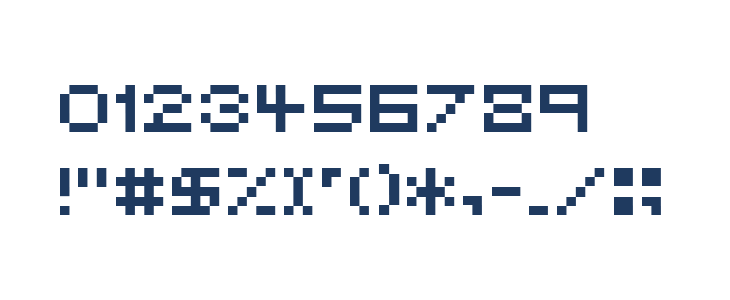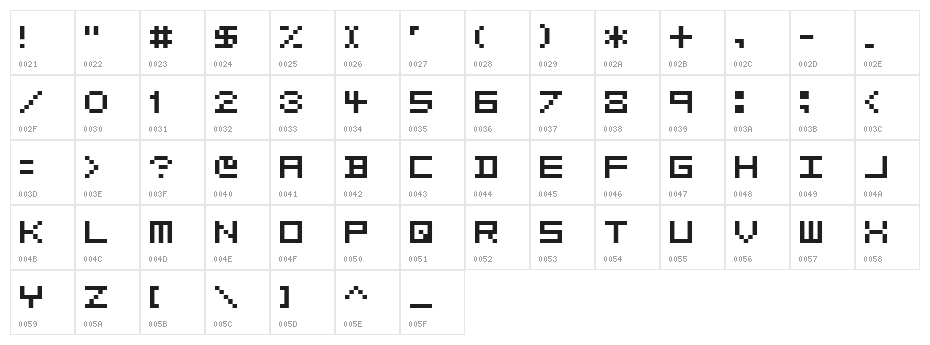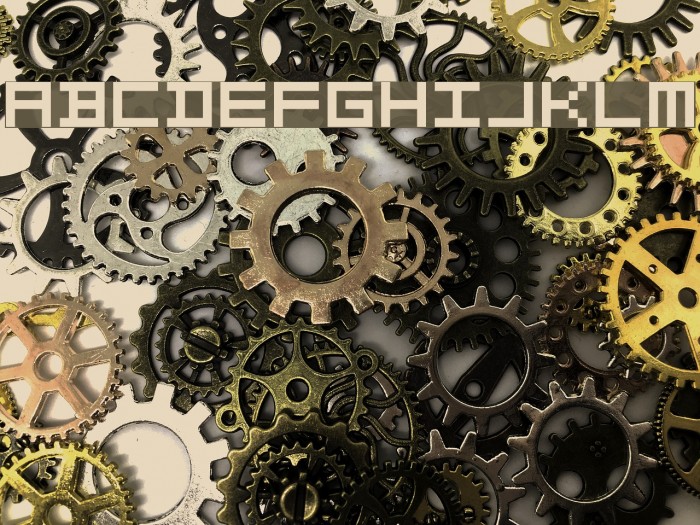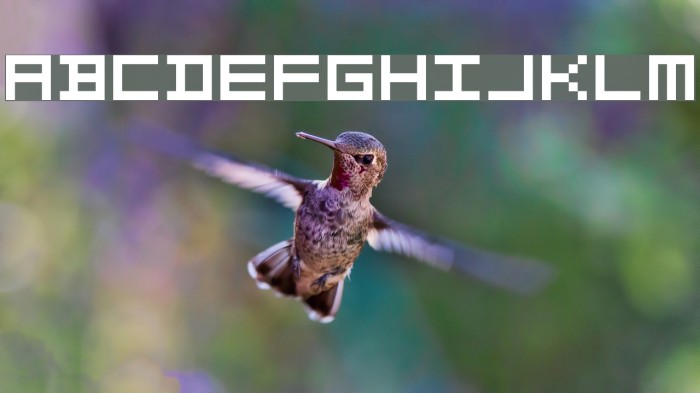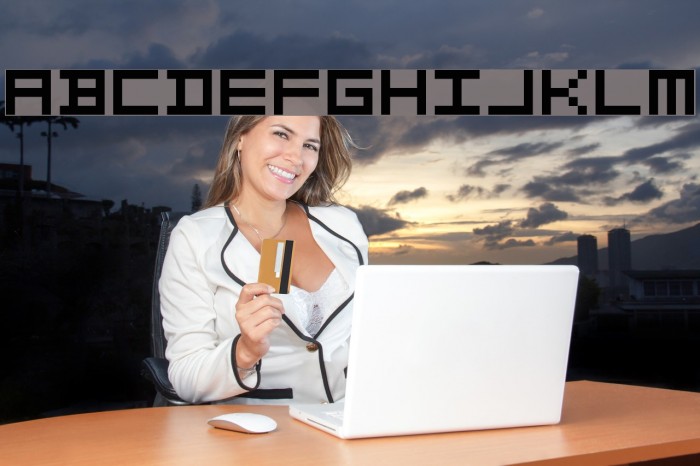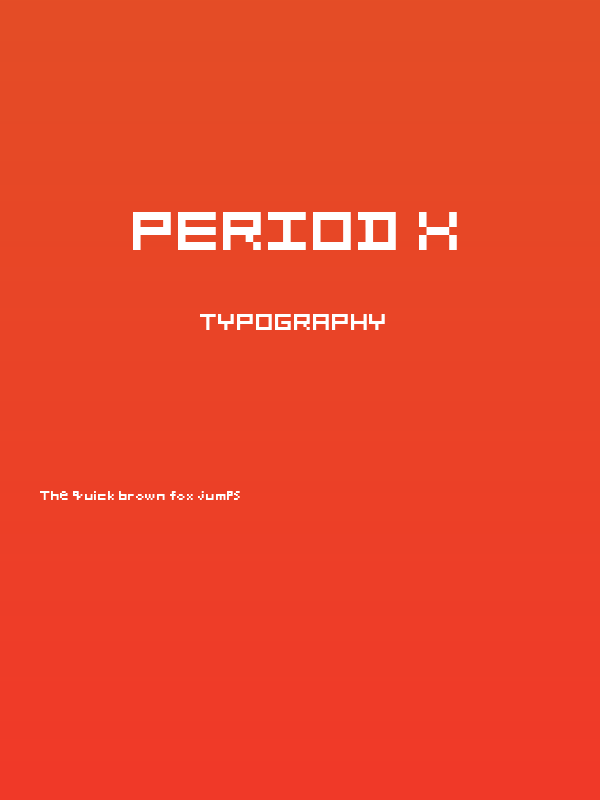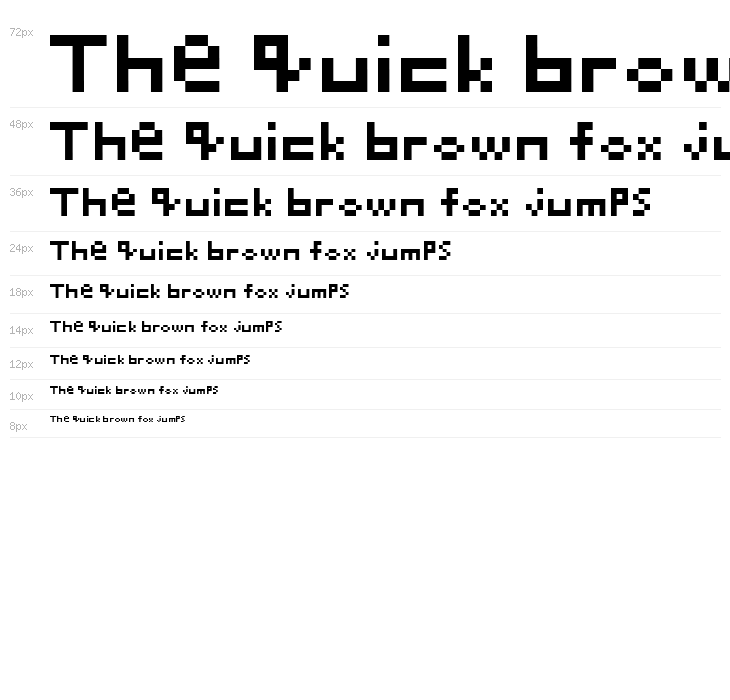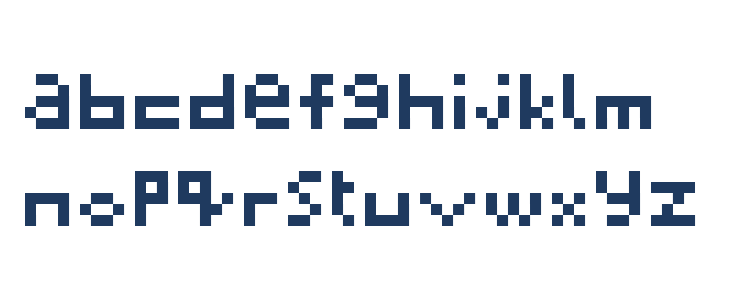
Period X Font
| 整体风格 | Retro, Digital |
| 推荐项目 | Ideal for video game design, retro-themed posters, digital art projects, and any creative work that seeks to evoke nostalgia for early computing and gaming eras. |